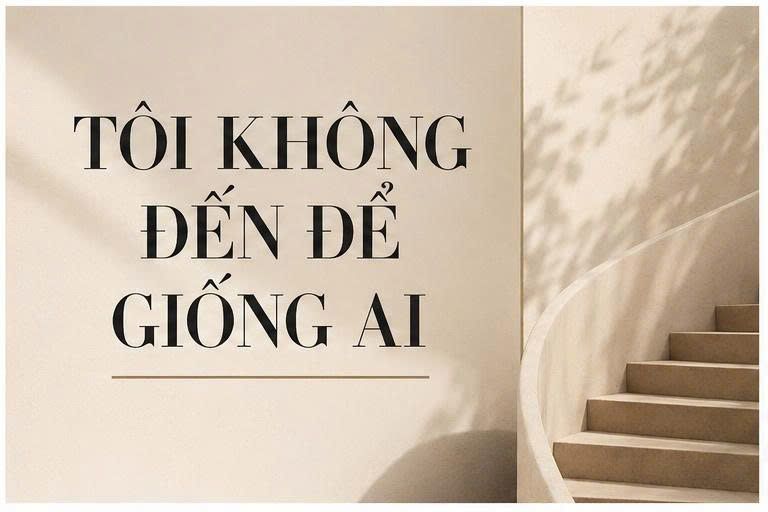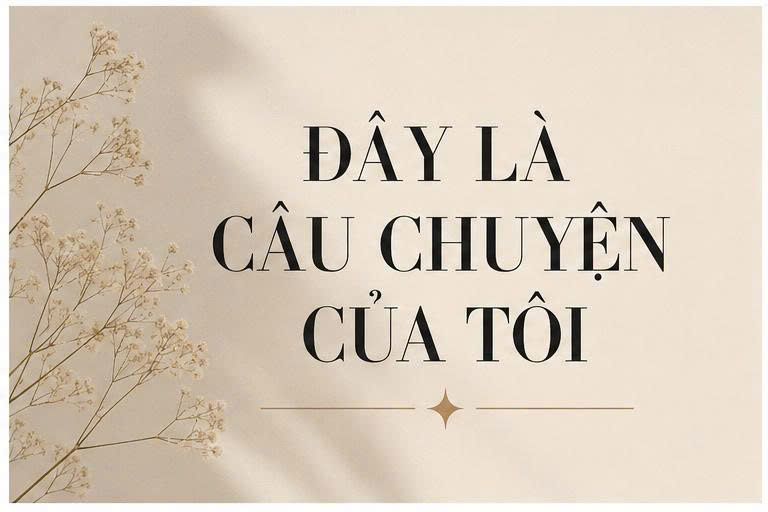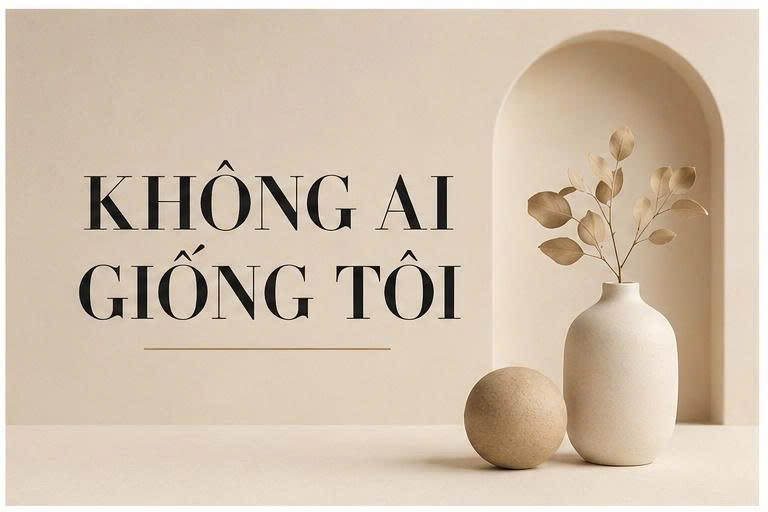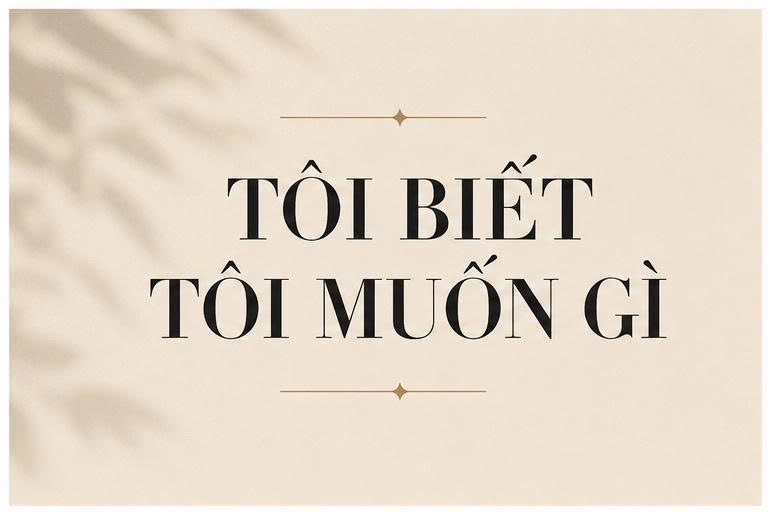
Font Bodoni Việt hóa là bộ phông chữ có chân (Serif) hiện đại thuộc nhóm Didone, nổi tiếng với vẻ đẹp sang trọng, quý phái và độ tương phản nét thanh đậm cực kỳ sắc sảo. Được thiết kế bởi Giambattista Bodoni vào cuối thế kỷ 18, phông chữ này đã trở thành biểu tượng của ngành thời trang cao cấp và các thương hiệu xa xỉ trên toàn thế giới. Doozypack.vn chia sẻ link tải font Bodoni Việt hóa chuẩn, giúp bạn sở hữu bộ font Bodoni tiếng Việt hoàn chỉnh để nâng tầm đẳng cấp cho các thiết kế bao bì và bộ nhận diện thương hiệu.
Đặc điểm thiết kế đẳng cấp của bộ font Bodoni Việt hóa
Bodoni không chỉ đơn thuần là một kiểu chữ; nó là kết quả của sự tinh chỉnh bậc thầy về tỉ lệ hình học, mang lại diện mạo vô cùng thời thượng và chuyên nghiệp.
Độ tương phản nét thanh đậm cực cao
Đặc trưng lớn nhất của font Bodoni Việt hóa là sự đối lập mạnh mẽ giữa các nét dọc dày dặn, vững chãi và các nét ngang thanh mảnh như sợi tóc (hairline). Cấu trúc này tạo nên một nhịp điệu Typography vô cùng lôi cuốn, giúp tiêu đề bản thiết kế của bạn toát lên sự tinh tế và đẳng cấp mà hiếm bộ font Serif nào có được.
Hệ thống chân chữ (Serif) phẳng và sắc sảo
Khác với các dòng Serif cổ điển có phần chân chữ hơi bo cong, Bodoni sở hữu phần chân phẳng và dứt khoát. Đặc điểm này kết hợp với trục chữ hoàn toàn thẳng đứng tạo nên một cảm giác minh bạch, quyền lực. Khi được Việt hóa tại Doozypack.vn, các bộ dấu tiếng Việt được xử lý tinh tế để không làm phá vỡ cấu trúc thanh mảnh của các nét ngang, đảm bảo tính thẩm mỹ đồng nhất.
Tại sao designer nên chọn font Bodoni tiếng Việt cho bao bì Luxury?
Trong ngành thiết kế và sản xuất bao bì tại Doozypack.vn, Bodoni luôn nằm trong danh mục các font chữ “quyền lực” nhất nhờ những ưu điểm vượt trội:
- Hoàn thiện nội dung tiếng Việt: Việc sử dụng bản Việt hóa chuẩn giúp bạn gõ các slogan như “Nước hoa cao cấp” hay “Thời trang thượng lưu” một cách trọn vẹn, không bị lỗi nhảy font ở các ký tự đặc thù.
- Tạo dấu ấn thương hiệu đắt tiền: Bodoni mang lại diện mạo “Premium” ngay lập tức, đặc biệt hiệu quả khi ứng dụng cho ngành mỹ phẩm, trang sức và rượu vang.
- Độ hiển thị sắc nét: Nhờ cấu trúc hình học chuẩn xác, Bodoni duy trì được vẻ đẹp sang trọng từ các bản vẽ trên màn hình đến khi xuất hiện trên chất liệu giấy thực tế.
Doozypack.vn cung cấp link tải bao gồm đầy đủ các biến thể từ Bodoni 72, Bodoni Poster đến các bản đặc biệt cho thiết kế in ấn chuyên nghiệp.
| Biến thể Font | Đặc điểm thị giác | Ứng dụng đề xuất tại Doozypack.vn |
| Bodoni Book/Regular | Thanh lịch, dễ đọc | Dùng cho nội dung mô tả, bảng thành phần trên vỏ hộp. |
| Bodoni Bold/Black | Mạnh mẽ, quyền lực | Dùng làm Logo, tên thương hiệu chính trên túi giấy cao cấp. |
| Bodoni Italic | Nghiêng, quyến rũ | Dùng cho các trích dẫn nghệ thuật hoặc ghi chú ngắn. |
Lời khuyên từ xưởng in: Do Bodoni có các nét ngang cực mảnh, bạn nên hạn chế in kích thước chữ quá nhỏ (dưới 8pt) trên các loại giấy có bề mặt thấm mực mạnh như giấy Kraft. Hãy ưu tiên in trên giấy Ivory phẳng mịn để nét chữ không bị mất chi tiết.
03 Ứng dụng của font Bodoni trong sản xuất bao bì tại Doozypack.vn
Vẻ đẹp quý phái của Bodoni mang lại hiệu quả thị giác đặc biệt trên các ấn phẩm tại Doozypack.vn:
- Hộp mỹ phẩm & Nước hoa: Sự kết hợp giữa Bodoni Regular và kỹ thuật ép kim mờ (Matte Gold) trên nền hộp tối màu tạo nên vẻ ngoài vô cùng đẳng cấp.
- Túi giấy thời trang cao cấp: Tên cửa hàng sử dụng font Bodoni in khổ lớn trên túi giấy Ivory cán màng mờ giúp khẳng định gu thẩm mỹ tinh tế của thương hiệu.
- Thiệp mời & Menu sự kiện: Nét chữ Serif sắc sảo của Bodoni là lựa chọn tuyệt vời cho các nhà hàng phong cách Âu sang trọng hoặc thiệp mời tiệc tối.
03 Lưu ý kỹ thuật khi in ấn font nét mảnh như Bodoni
Sản xuất bao bì sử dụng phông chữ có độ tương phản cao như Bodoni đòi hỏi designer cần lưu ý một số vấn đề kỹ thuật tại xưởng in chuyên nghiệp:
- Gia công ép kim và dập nổi: Các nét hairline của font Bodoni có thể không bám nhũ nếu khuôn ép không được xử lý kỹ. Bạn nên tăng nhẹ độ dày nét chữ (Stroke) khoảng 0.05pt trước khi làm khuôn để đảm bảo độ sắc nét.